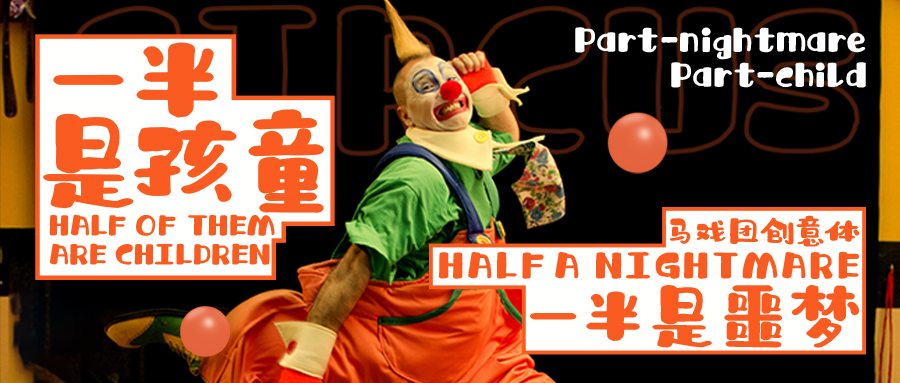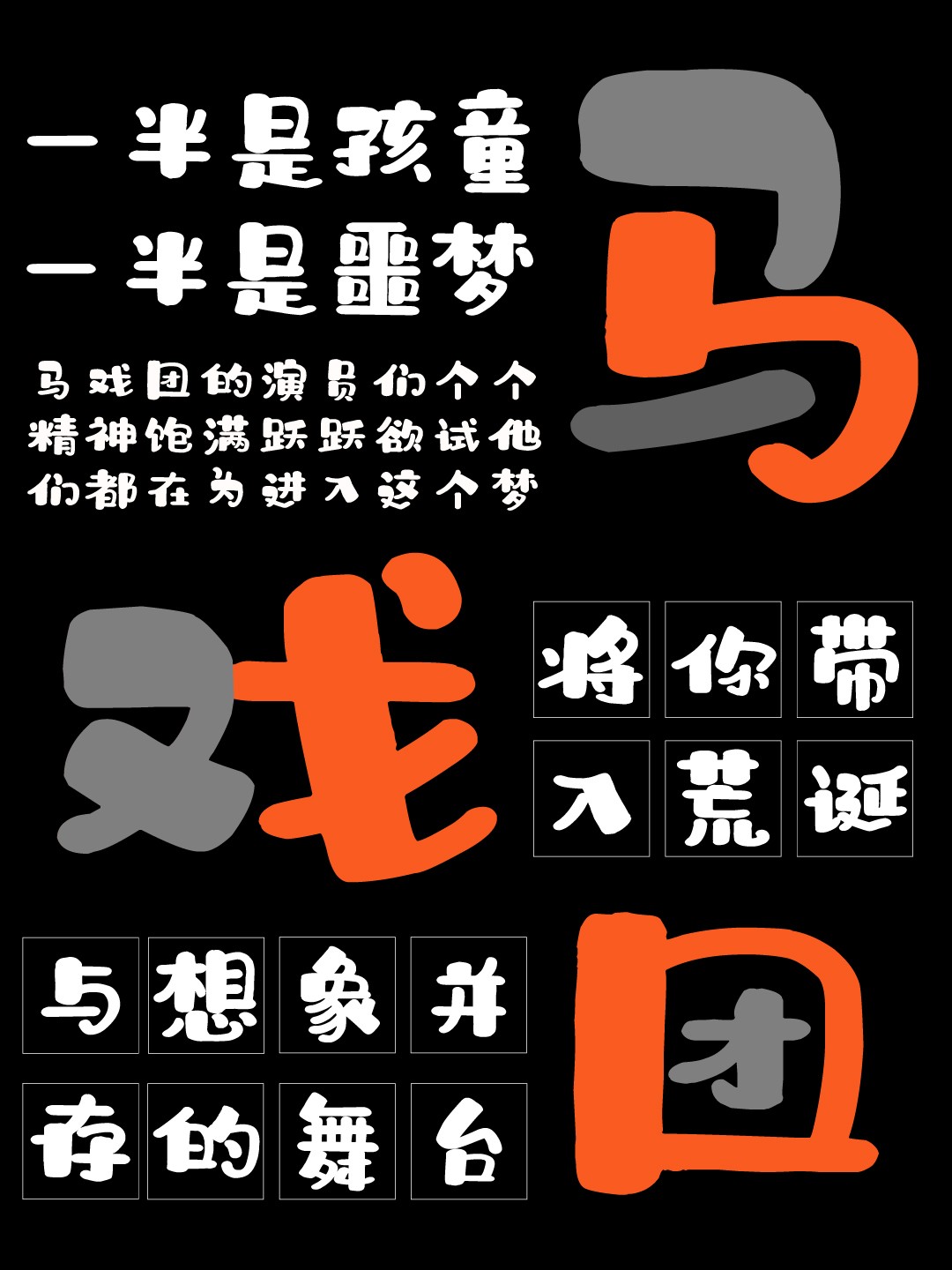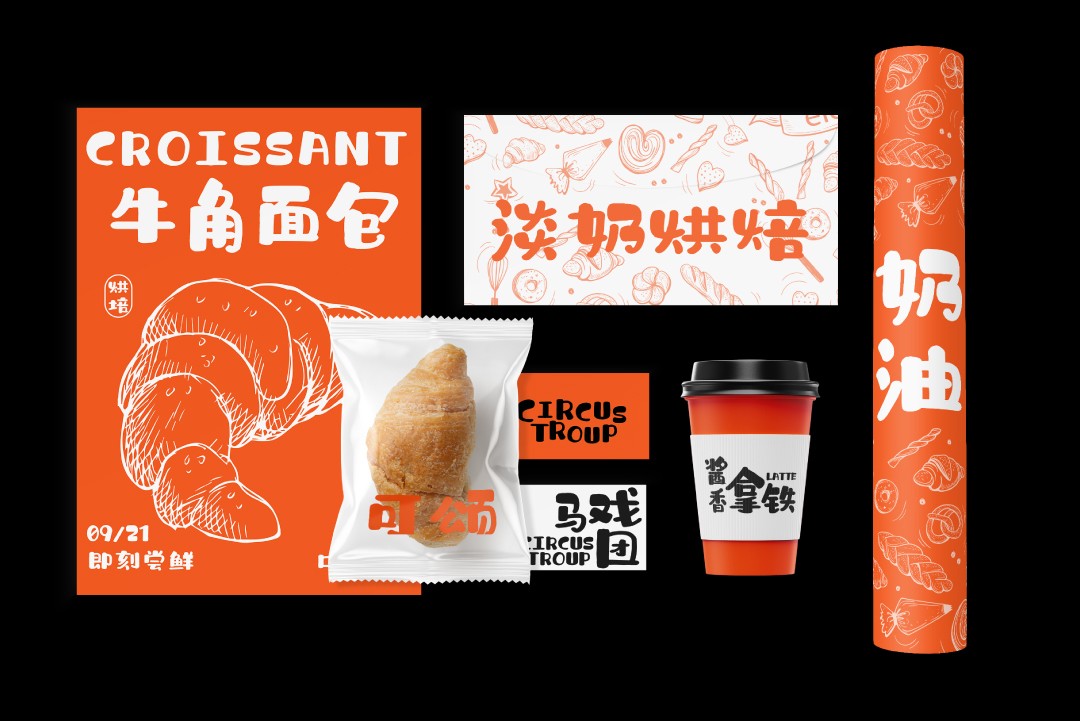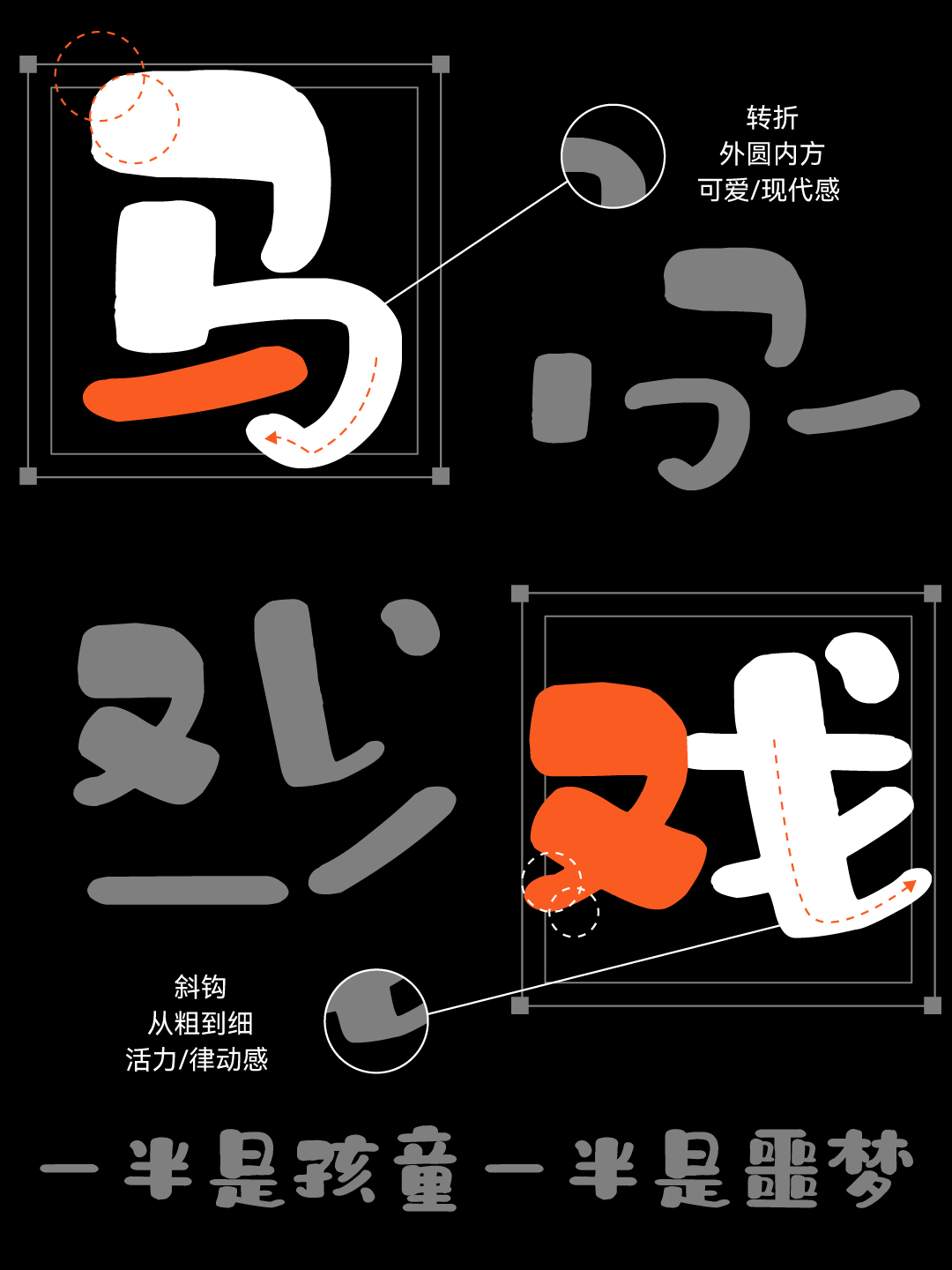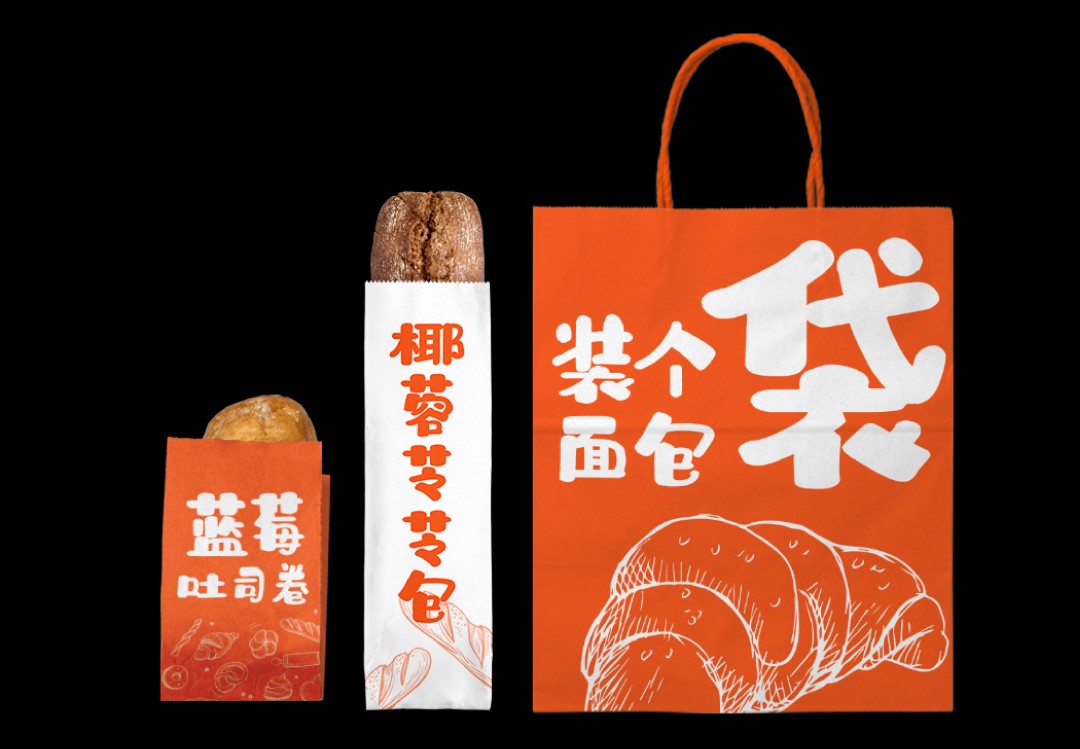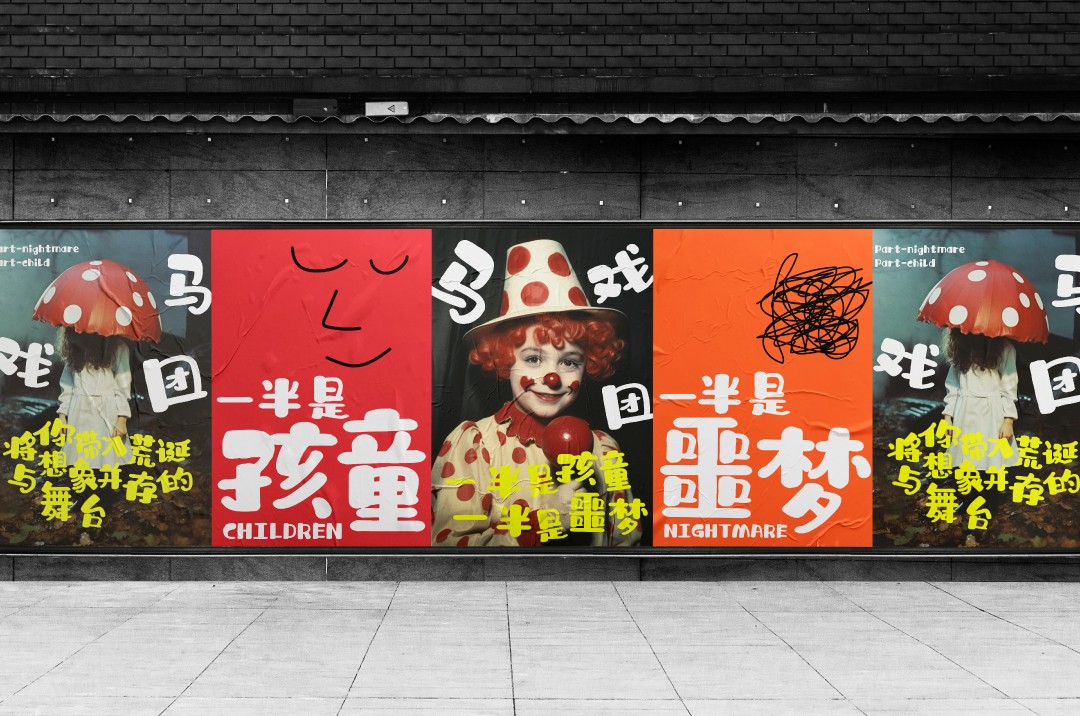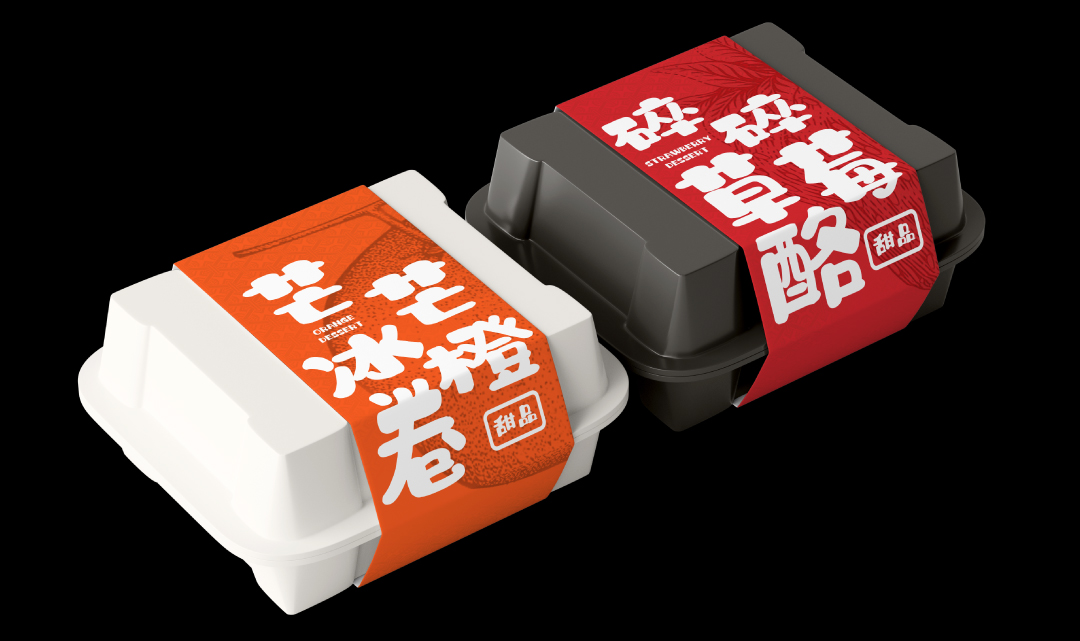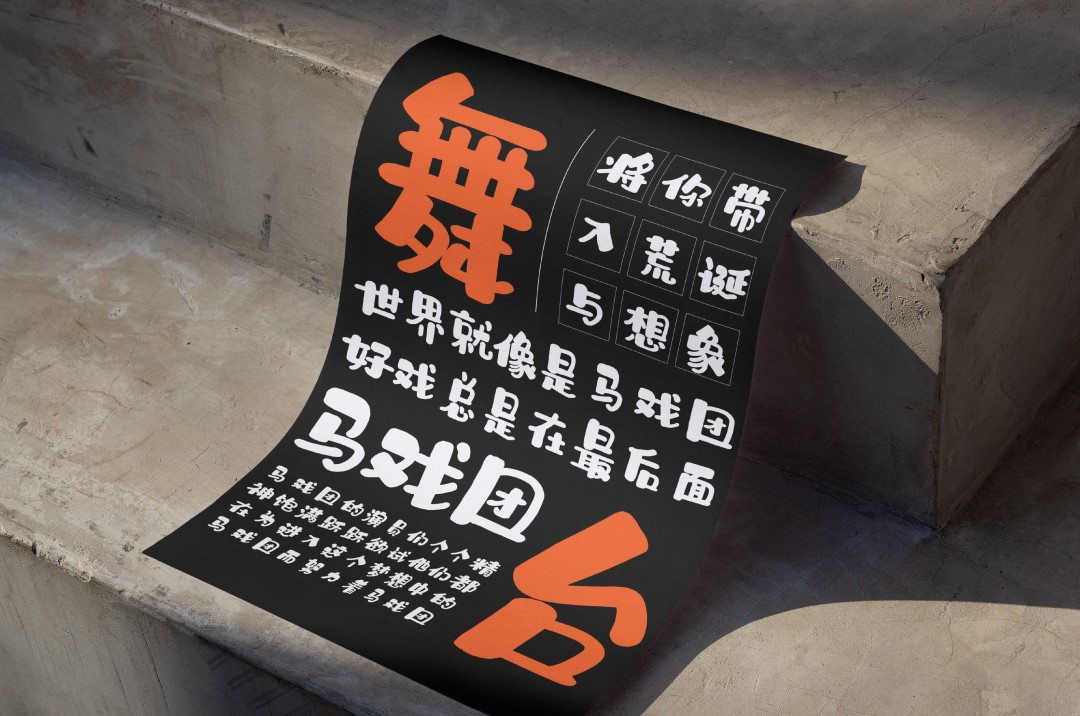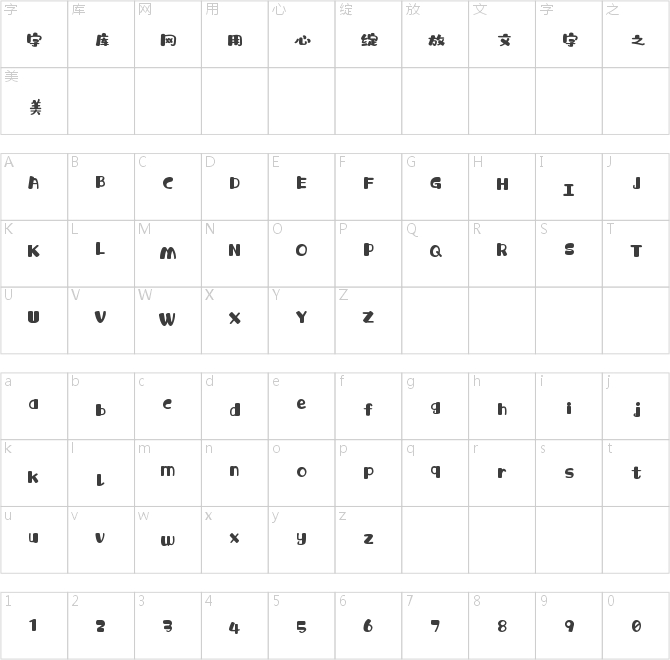
字体名称: 也字工厂马戏团
也字工厂马戏团创意体
「也字工厂马戏团创意体」将你带入荒诞与想象并存的舞台h of i
字体立意:
何怀宏在《比天空更广阔的》中写过一句话:
“生命在边缘处反而愈加显示其意义和深刻”。
马戏舞台是小丑的主场,戏终人离去,聚光灯渐暗,摘下彩色假发和红鼻子的道具的这一刻小丑回到现实;《千与千寻》中阴郁沉默的无脸男成为众人避之不及的角色,无脸男属于现实社会,但是又游离于现实社会,当无脸男被千寻的真诚所感化而褪去体内的污垢之后,我们看到了令人温暖的人性。各就各位,当聚光灯再次打在小丑的身上,一场滑稽的表演再次拉开序幕,生活是一场循环的恶搞。
这也是「也字工厂马戏团创意体」的立意碎片之一,我们想通过这款字体传达某种信念。
比如 黎明前夕的氤氲,郁郁寡欢的玩笑,沉默不语的力量
字体特点:
「也字工厂马戏团创意体」以其整体效果及特殊的字形而备受瞩目。字形略扁,粗细对比明显,圆润饱满,让每个字形都富有节奏变化。它带来一种活泼可爱的形态,似乎立刻散发出浓郁的欢乐气息。每个字的笔画粗细处理灵活多变,对比夸张,转折的笔画都带有弧线,使整体字体显得古灵精怪。
笔画特征笔画粗细灵活处理,对比夸张,转折的笔画都有弧线,显得轻松不死板。
结构特征:结构灵活多变,字面宽窄高低随字形变化而变化。在轻松的氛围中营造出天真烂漫的感受。
应用领域标志/广告 / 包装/ 影视/ 游戏/绘本
字体风格趣味、轻松、可爱
笔画亮点:「转折」与「斜勾」的“巧”与“妙”
「转折」
笔画转折采用了外圆内方的设计。笔画在转折点处呈现出典型的圆润外部,但内部边缘是类似方形的造型。这种设计风格结合了圆润和角度分明的特点,使字形看起来既可爱又具有一定的现代感。
「斜勾」
这个笔画造型的特点是从粗到细的斜线,它们具有一种动态感和生气。笔画从一侧开始,然后逐渐变细,形成了斜勾的效果。这种设计为字体赋予了一种活力和律动感。
总而言之,「也字工厂马戏团创意体」以独特的字形特点、整体效果和灵动性,在广泛的应用领域中都能带来令人愉悦的视觉体验。
它将标志设计、广告制作、包装设计、影视创作、游戏开发和本创作提升到一个全新的水平,为每个项目都来无穷的可能性。希望能有更多热爱设计的伙伴来体验它带来的独特魅力和创意灵感。